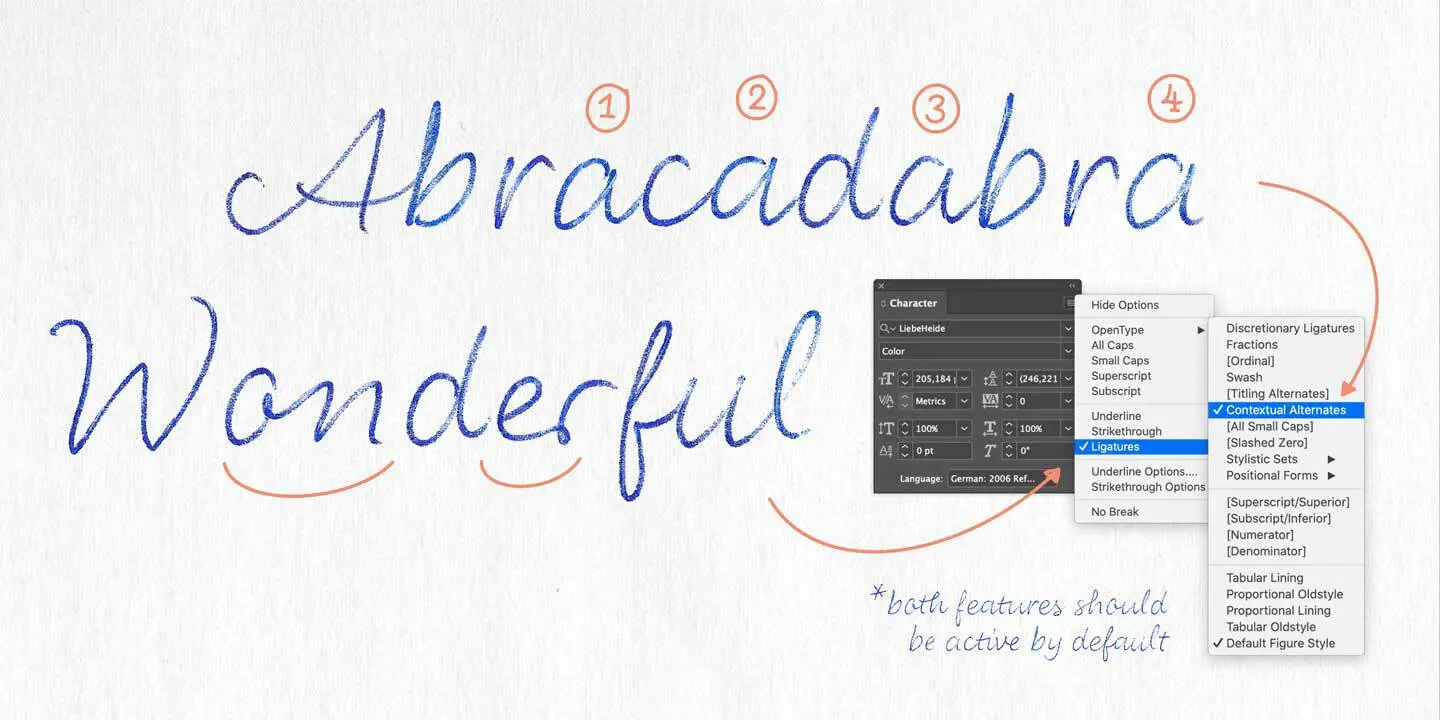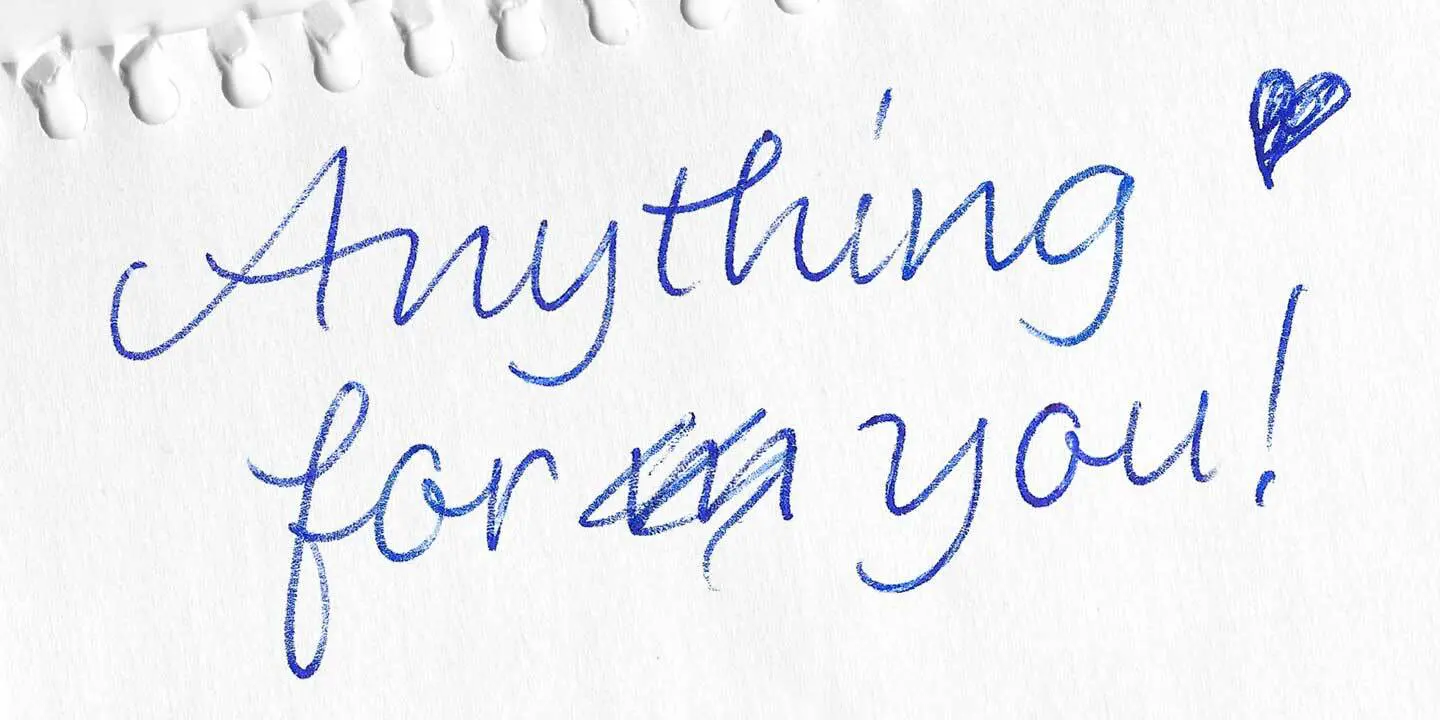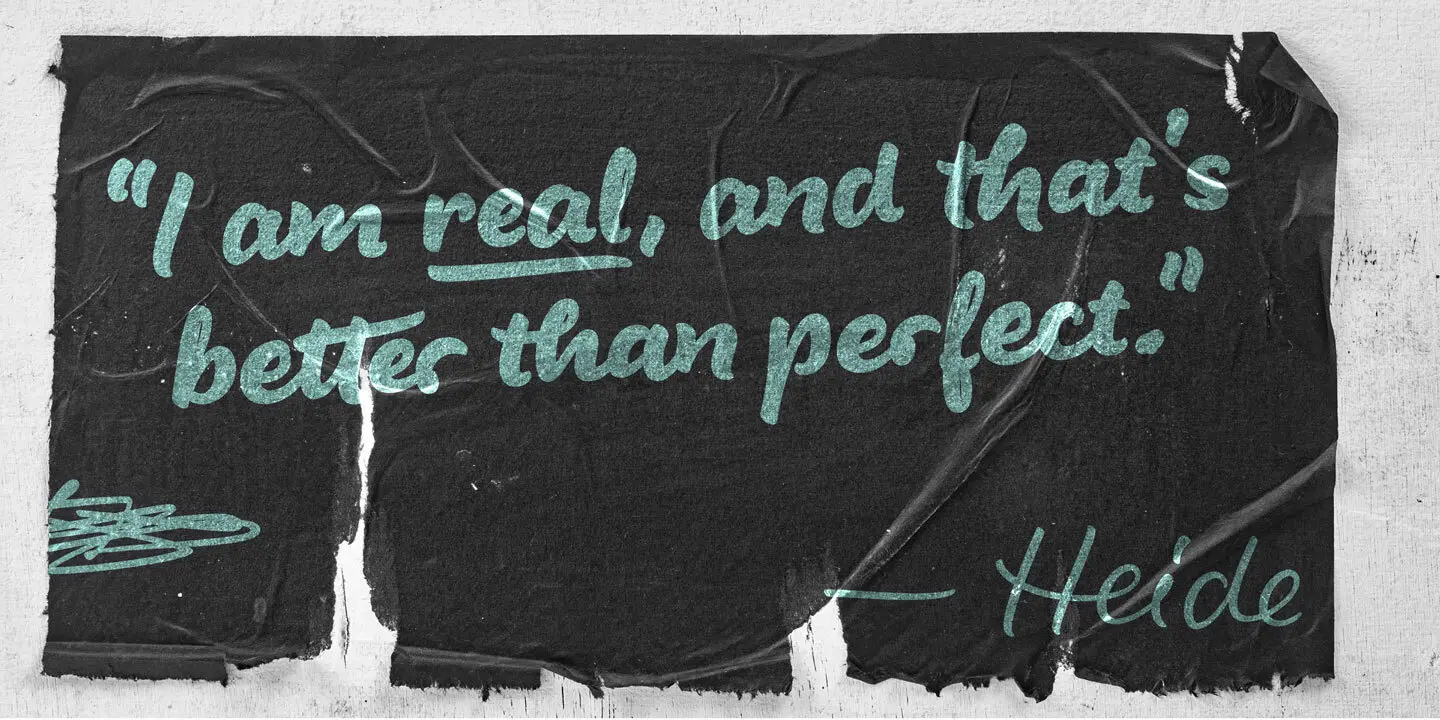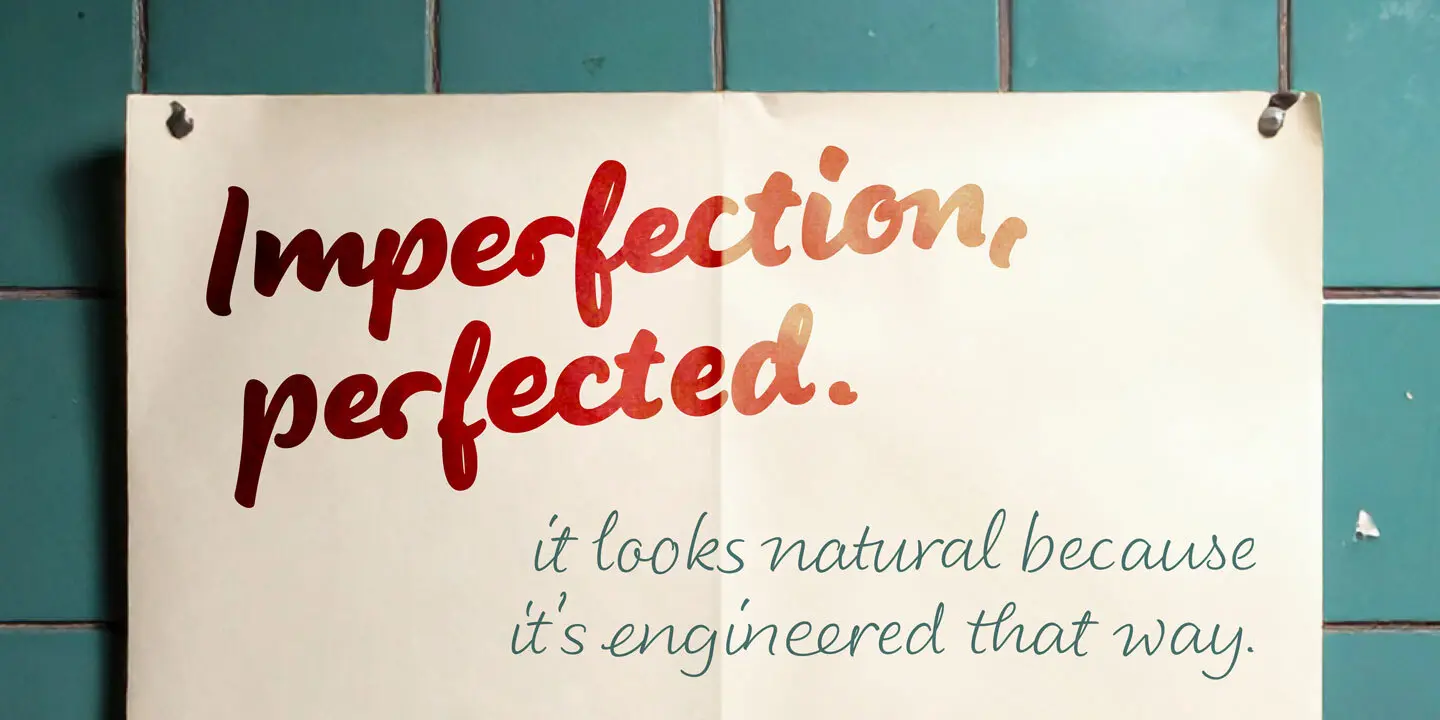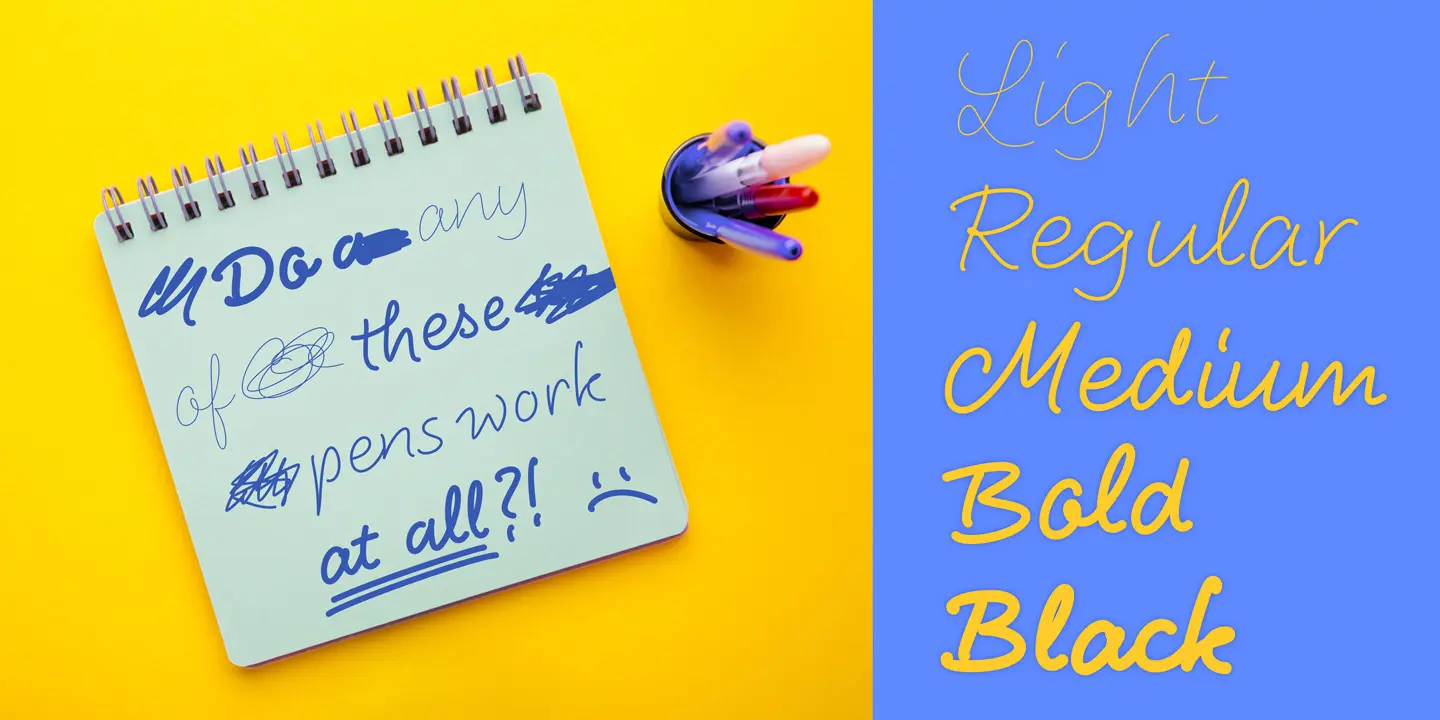
Die LiebeHeide ist eine verbundene Schreibschrift von Ulrike Rausch. Die Schrift erschien ursprünglich 2020 als pixelbasierte farbige Schrift, die durch die Pixeldarstellung und OpenType-Funktionen das Schreiben mit einem Kugelschreiber möglichst exakt simuliert.
2024 wurde die LiebeHeide Fineliner nachgelegt, die den Stil als reguläre, vektorbasierte OpenType-Schrift umsetzt und in fünf Strichstärken oder einer variablen Schrift verfügbar ist.
2025 erschien die LiebeHeide Brush. Hier werden die Buchstabenformen der LiebeHeide als Pinselschrift mit entsprechendem Duktus in fünf Strichstärken umgesetzt.